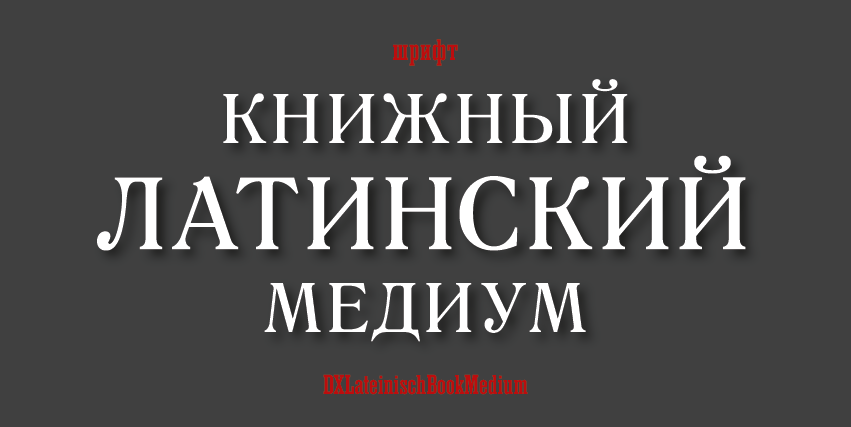
Шрифт Латинский книжный Медиум/LateinischBookMedium
Выпущен шрифт DXLateinischBookMedium. Версия шрифта разработана на основе гарнитуры "Латинская", словолитного заведения Г.Бертгольда (С.-Петербург). Текстовый антиквенный шрифт.